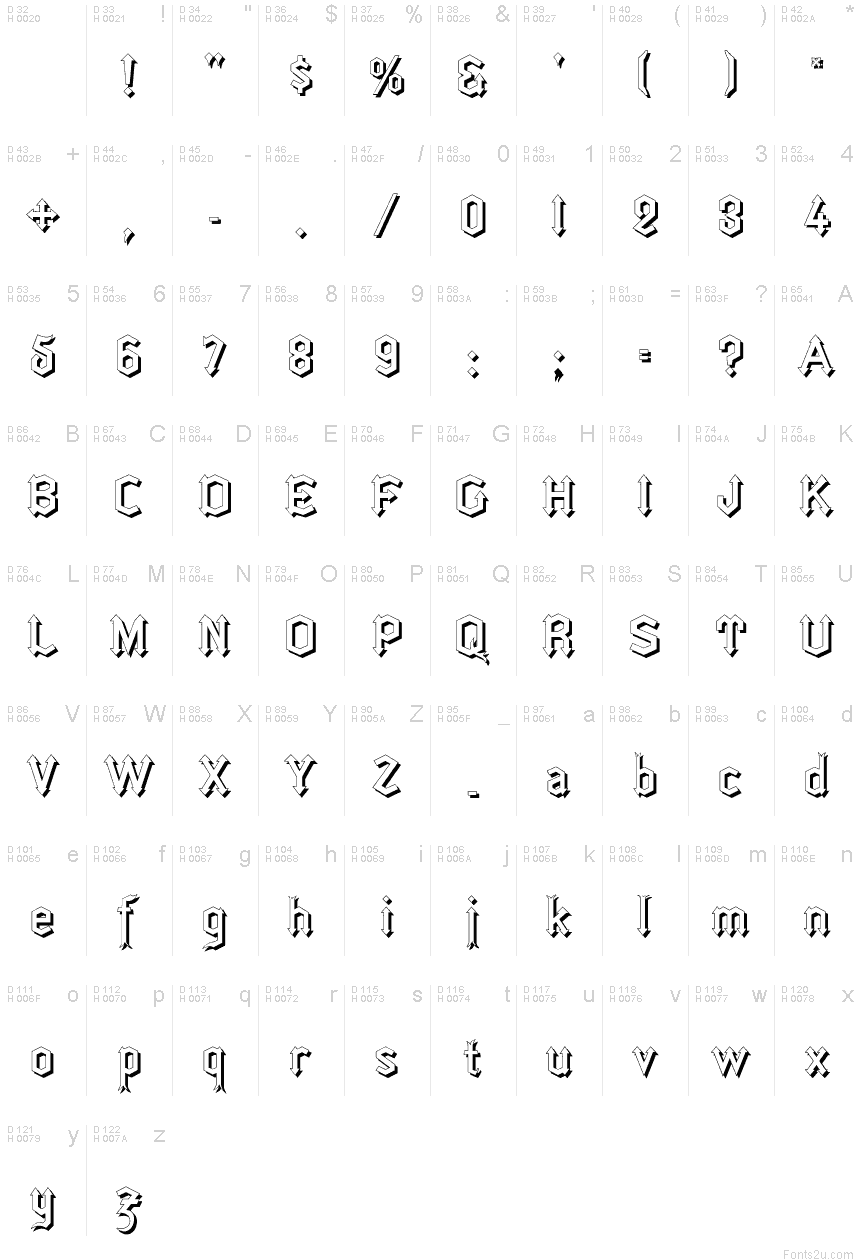
Arrowhead Lake Sunlit to darmowy krój tekstowy 3D z konturem. Jej wysokie, kanciaste majuskuły łączą cienkie kontury zewnętrzne z solidnymi, przesuniętymi cieniami. Ostro zakończone szeryfy i groty przypominające groty strzał nadają literom ostro wyciętą, emblematyczną sylwetkę.
Producenci odzieży outdoorowej i miejsca w stylu western mogą go używać do szyldów, gadżetów i plakatów wydarzeń o surowym, vintage'owym charakterze. Może przekształcić nazwę marki w emblemat przypominający odznakę.
Based on Arrowhead from the Solotype Catalog and alphabet books. Scanned and created by Character. All rights waived.